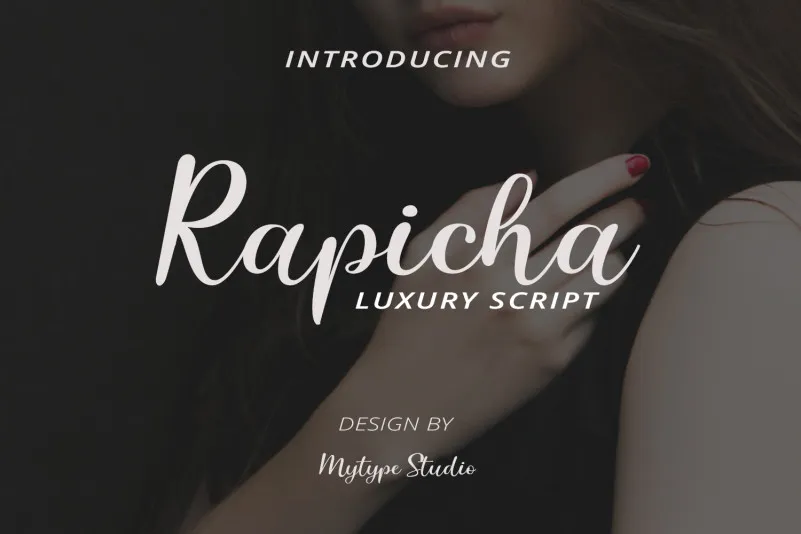
Rapicha Font – Download Grátis
A ‘Rapicha Font’ é uma elegante fonte escrita a mão que manteria fiel às influências do calligrafista, ao mesmo tempo que proporcionaria um toque contemporâneo e inovador à sua utilização. Criada pelo designer Icreatype, ela oferece aos criadores de design a oportunidade de incorporar personalidade e sofisticação em seus projetos. Uma fonte como essa não apenas reflete o encanto do handwriting elegante, mas também transmite uma sensação fresca e atual. Ideal para designers que valorizam uma mistura perfeita entre história e modernidade, a ‘Rapicha Font’ é certamente um tesouro a ser explorado em qualquer projeto de design.